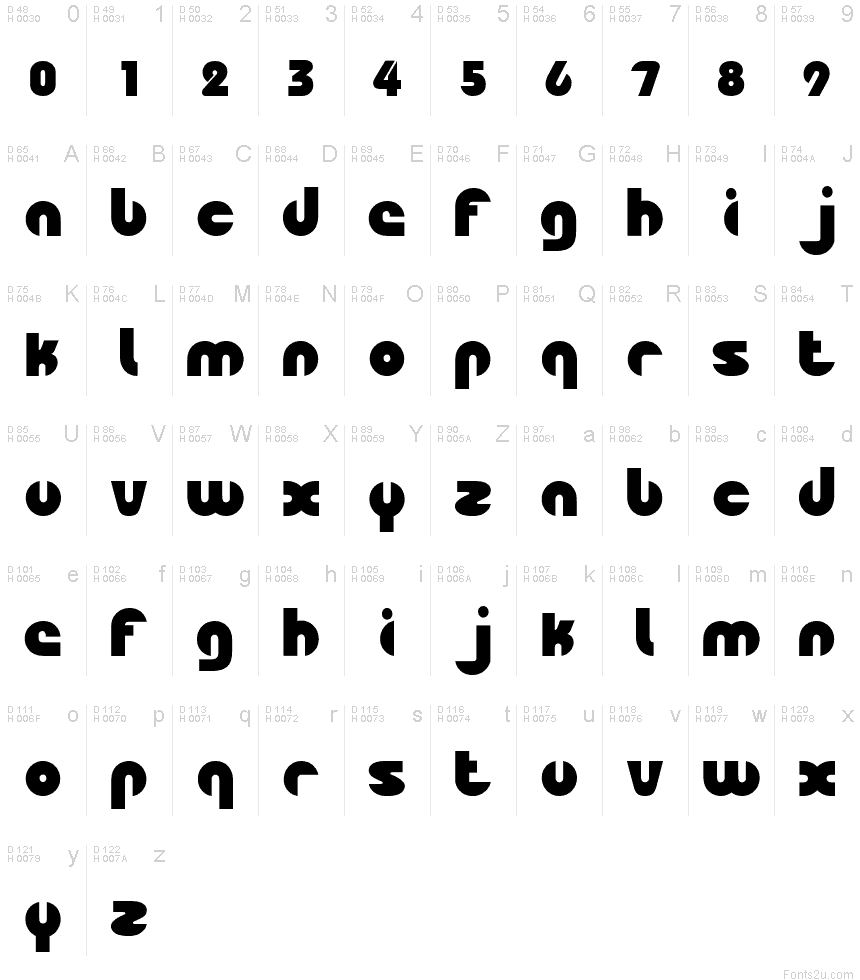
Fingerpop von Flava Fontz ist eine kostenlose, groovige Display-Schrift, die einschlägt wie eine Bassline – dick, rund und voller Energie. Ihre bulligen Kurven und der straffe Rhythmus sorgen für markante, blockartige Schriftbilder, die gleichzeitig retro und modern wirken: wie 70er-Jahre-Funk, neu gemixt für heute. Die Buchstaben greifen fast modular ineinander und verleihen deinen Überschriften eine kraftvolle, geschlossene Silhouette, die garantiert auffällt.
Mit Fingerpop bringst du Energie auf Musikposter, Club-Flyer, Streetwear-Marken, auffällige Verpackungen, Social-Media-Grafiken und verspielte Logos. Diese kostenlose Schrift glänzt vor allem in großen Formaten, wo ihre tintigen Kurven und tiefen Punzen richtig zur Geltung kommen. Kombiniere Fingerpop für den Begleittext mit einer schlichten, schmalen serifenlosen Schrift, damit der Fokus auf den fetten, groovigen Buchstabenformen bleibt.